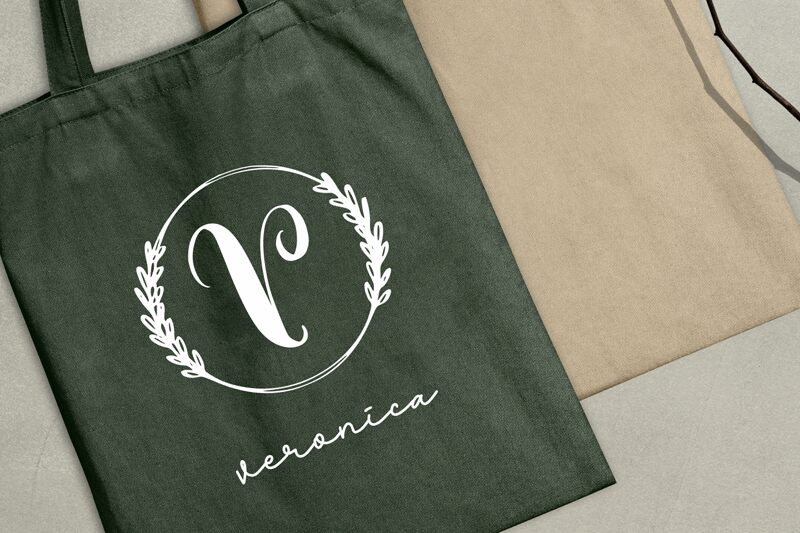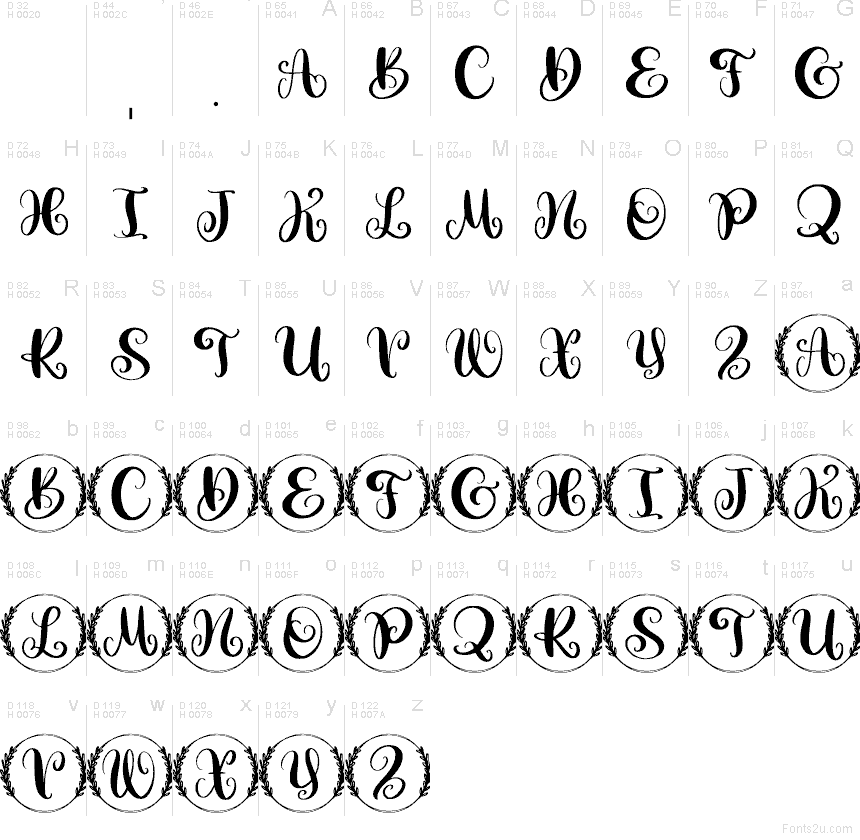
Amilie
Amilie, créée par Abo Daniel, est une police de caractères décorative de type « display » aux lettres calligraphiques fluides entourées de couronnes de lauriers. Les traits se terminent par de longues boucles et des finitions soignées, donnant à chaque caractère un aspect de monogramme encadré plutôt qu'un rythme de texte classique.
Amilie est idéale pour vos faire-part de mariage, logos, emballages de boutique, menus d'événements et badges pour réseaux sociaux, où les détails en forme de couronne peuvent servir d'emblème central ou d'accent visuel. Cette police gratuite s'adapte aussi parfaitement aux marque-places, étiquettes saisonnières et titres lorsque vous recherchez une typographie qui fait partie intégrante de l'ornementation.